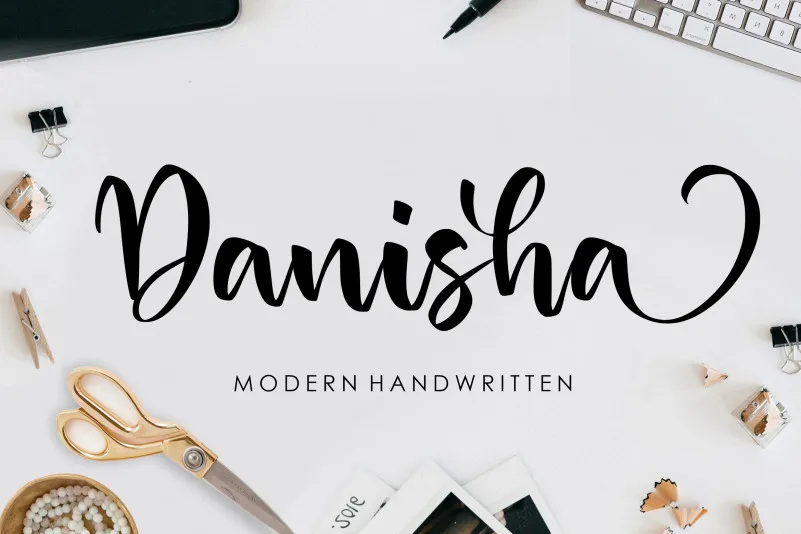
A fonte Danisha é perfeita para criar designs originais e únicos que transmitem uma sensação envolvente. Suas letras curvilíneas e texturas suaves fornecem um tom natural e aconchegante, ideal para aplicar em diversas categorias de projetos gráficos. Este design cuidadosamente elaborado é perfeito tanto para enriquecer a identidade visual das embalagens de produtos, quanto para projetos de marca. Suas linhas leves e delicadas também são ideais para capas de revistas ou editoriais, tornando o seu conteúdo ainda mais chamativo. A fonte Danisha tem um estilo que se adapta perfeitamente a mídias sociais, especialmente ao criar posts com textos bonitos e elegantes. Ela é tão versátil quanto para cartazes de eventos, como casamentos ou outros tipos de grandes ocasiões, onde o seu equilíbrio suave pode contribuir significativamente para sua apresentação. Com a Danisha na sua paleta de ferramentas, você terá uma fonte perfeita para expressar textos em fundos mais complexos, como texturas ou imagens de alta resolução. É a escolha ideal para pessoas que querem criar ambientes visuais atraentes e confortáveis que não deixam os olhos da sua audiência indiferentes.